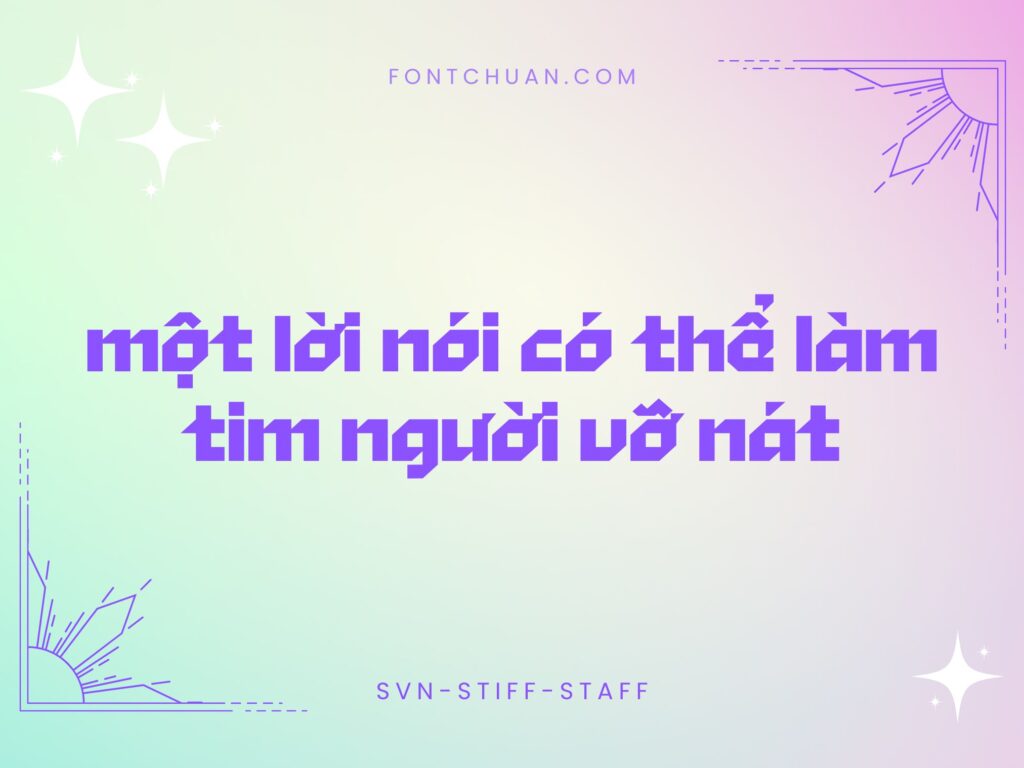
Font SVN Stiff Staff là phiên bản Việt hóa của kiểu chữ Stiff Staff, được thực hiện bởi STYLEno.1 Fonts. Đây là một font chữ hiển thị độc đáo, được thiết kế bởi Borislav Alexandrov và phát hành bởi Fontfabric. Stiff Staff chỉ bao gồm chữ in thường, với các nét chữ vuông vức kết hợp với các góc vát nhọn sắc bén, tạo nên vẻ mạnh mẽ và hiện đại. Font này phù hợp cho các thiết kế về trò chơi điện tử, hoạt hình và các dự án sáng tạo khác.
SVN Stiff Staff lý tưởng cho các dự án thiết kế yêu cầu sự mạnh mẽ và cá tính, như thiết kế logo, tiêu đề, bao bì sản phẩm và các ấn phẩm truyền thông. Các ngành nghề như quảng cáo, công nghệ và giáo dục có thể tận dụng font này để tạo điểm nhấn trong thiết kế. Ngoài ra, font cũng thích hợp cho các sự kiện như Tết, Giáng sinh, Halloween và các lễ hội khác.